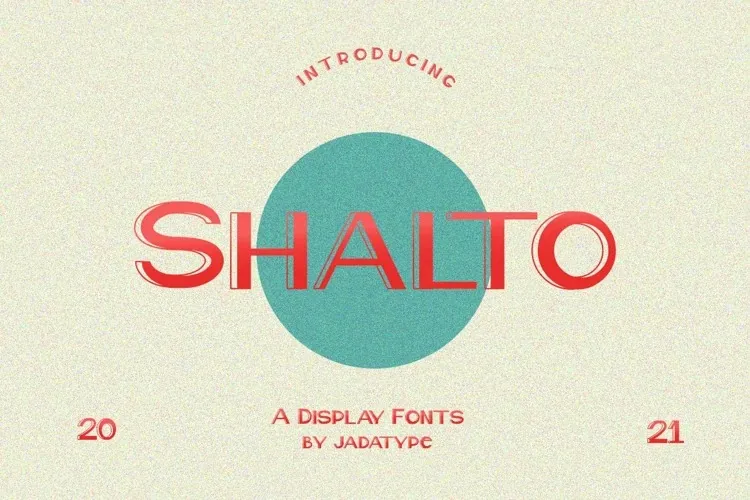
A Shalto Font é uma elegante escolha para designers que buscam criar ambientes vintage contemporâneos. Especificamente desenvolvida para aconselhar e ilustrar textos de mídia corporativa ou publicitária com um visual despojado, este tipo de fonte sans serif é perfeita para aplicativos como Adobe, Affinity e até mesmo o Word. Com seu estilo limpo e minimalista, a Shalto Font permite que designers criem ambientes vintage sem abrir mão do conforto moderno. Suportando letras em inglês padrão e algumas variantes multilínguas, esta fonte pode ser utilizada em uma variedade de projetos, desde cartazes até capas de livros ou até mesmo para criar identidade visual única para marcas de produto. Seja você um designer gráfico experiente buscando adicionar algum estilo clássico a seus trabalhos, ou alguém que está apenas começando e busca uma ferramenta versátil, a Shalto Font é perfeita para ajudar a ilustrar suas ideias. Sem dúvida, esta fonte será uma excelente adição ao seu arsenal de recursos gráficos.